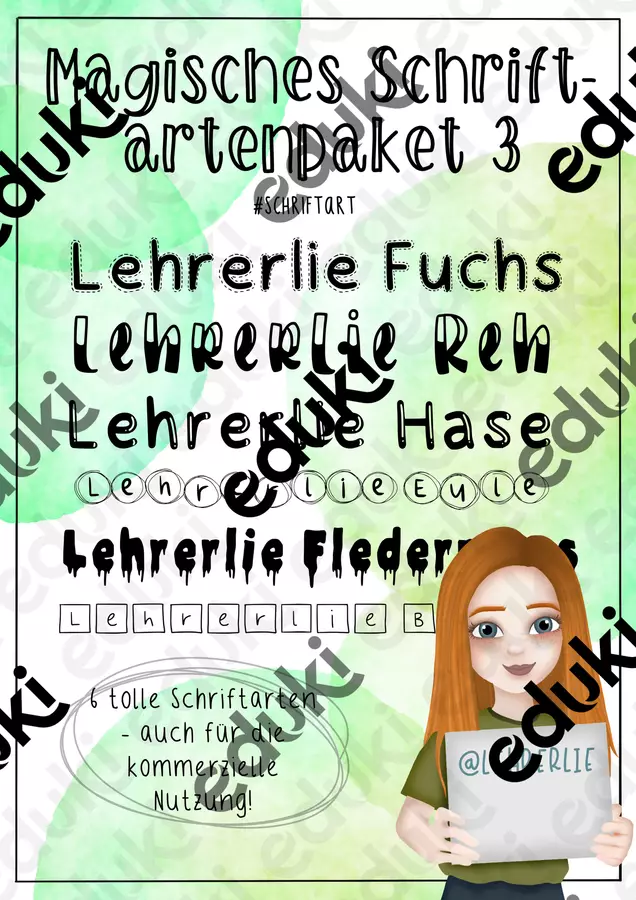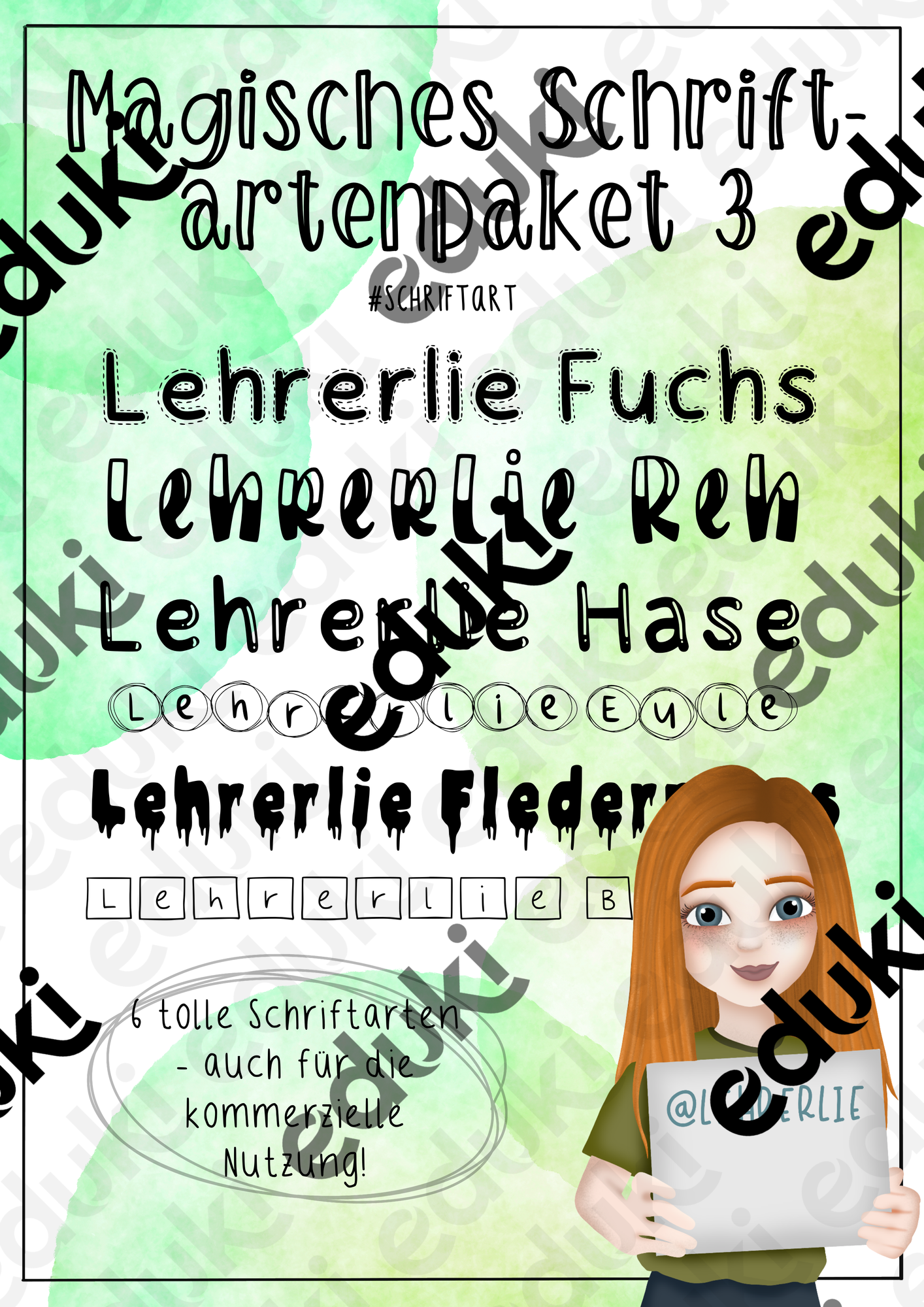
Wuhuuu! Neben Paket 1 und Paktet 2, welche schon einige tolle Schriftarten enthalten, folgt nun endlich das magische Schriftartenpaket 3! Hier erhaltet ihr wieder 6 (Über-)Schriftarten, mit den wichtigsten deutschen Schriftzeichen - die machen sich einfach auf jedem Arbeitsblatt wunderbar :-)